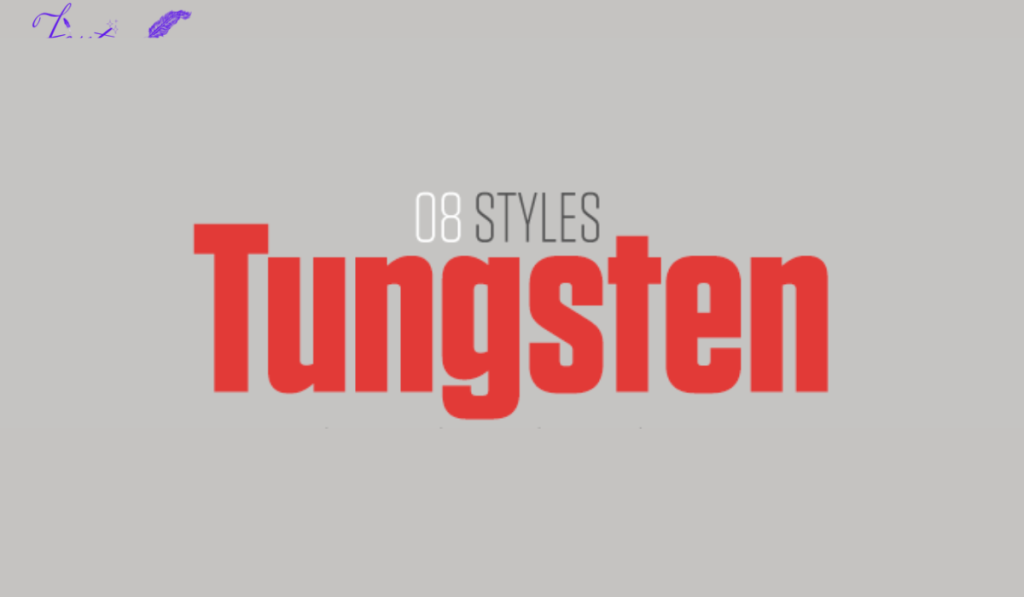
Font SVN Tungsten
Phân loại: Hiện đại, tinh tế
Kiểu chữ: Sans-serif
Độ dày: Thin, Regular, Bold
Font SVN Tungsen là kiểu chữ không chân thuộc font SVN, thường được dùng làm văn bản của báo chí, tạp chí.